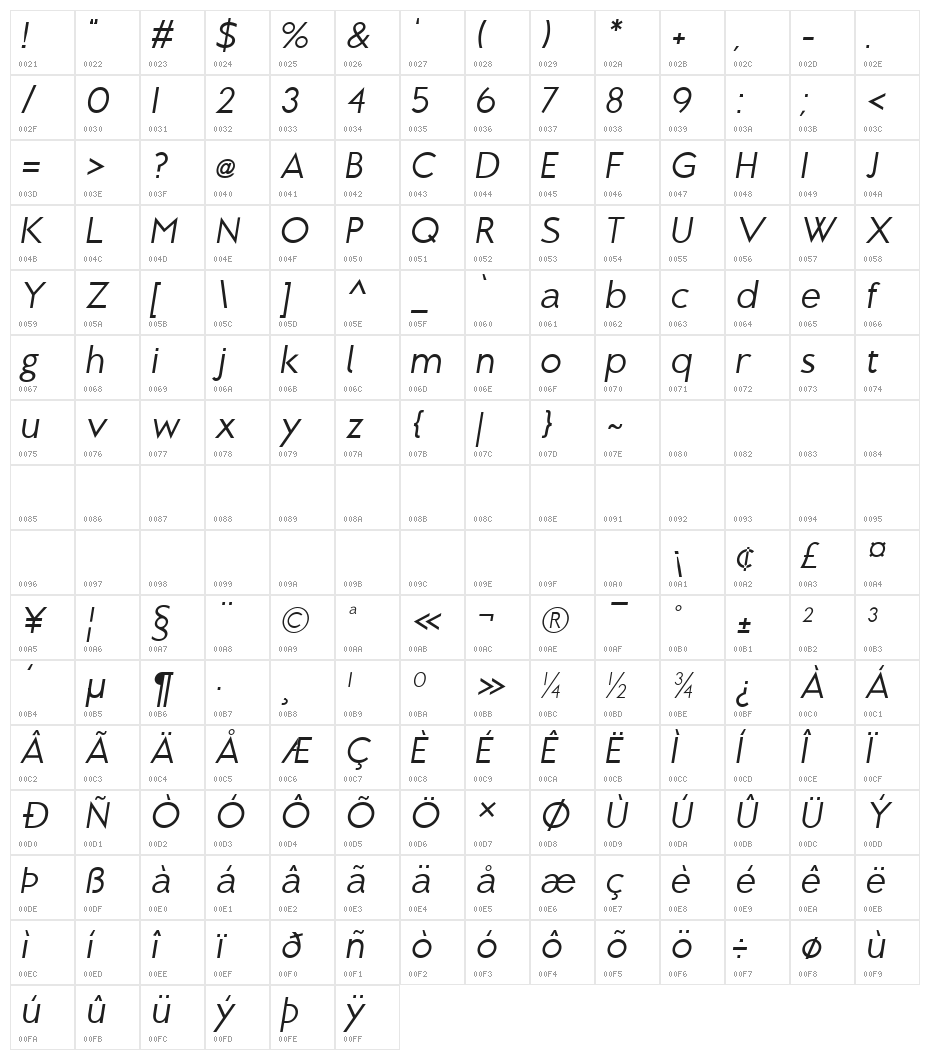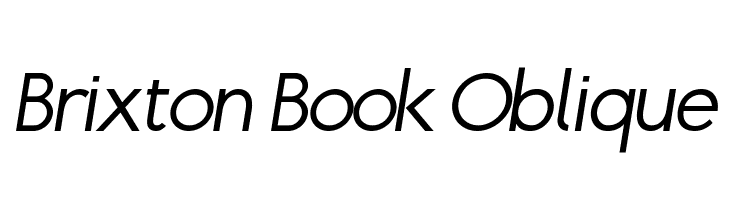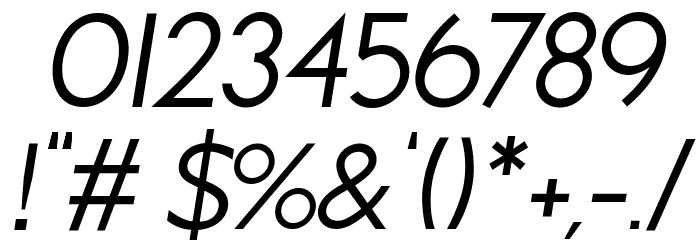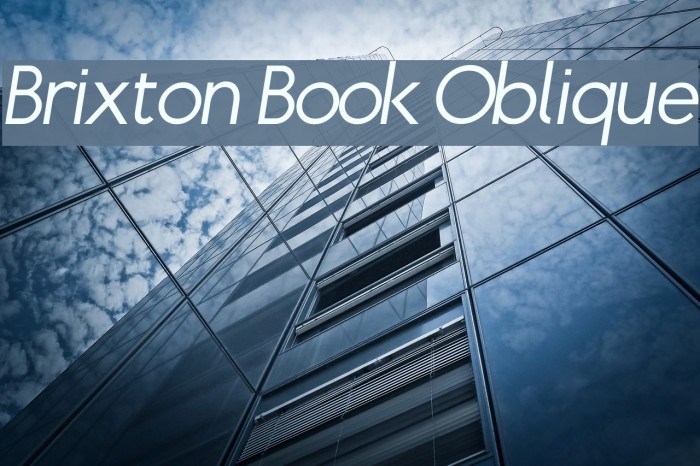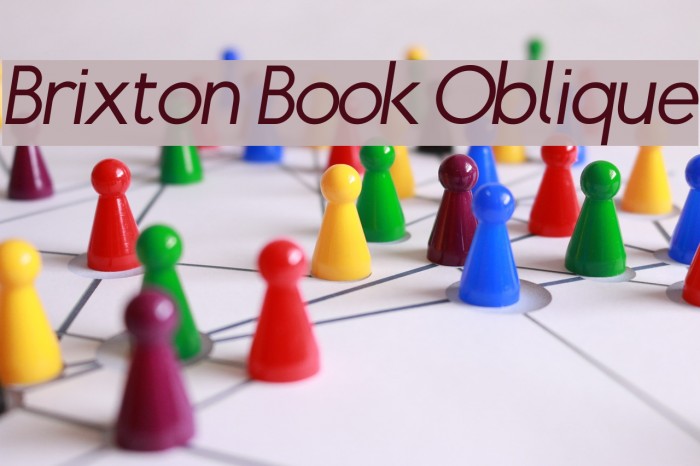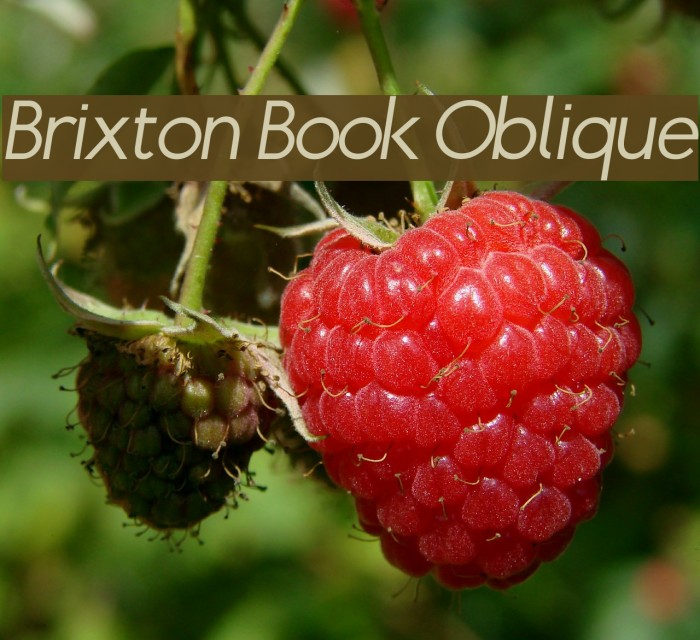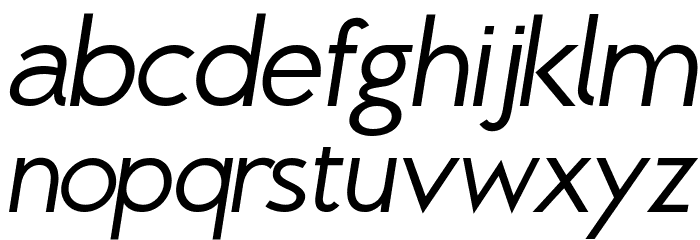
Brixton Book Oblique Font
✎ Modern
| Categorías | Modern |
| Caso de uso | Headlines, Body text, Logos |
| Proyectos propuestos | Ideal for branding, advertising, web design, and editorial layouts where a modern and sleek appearance is desired. |